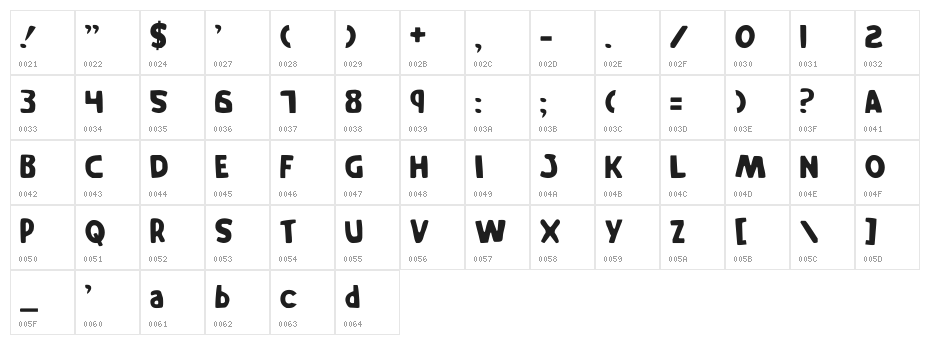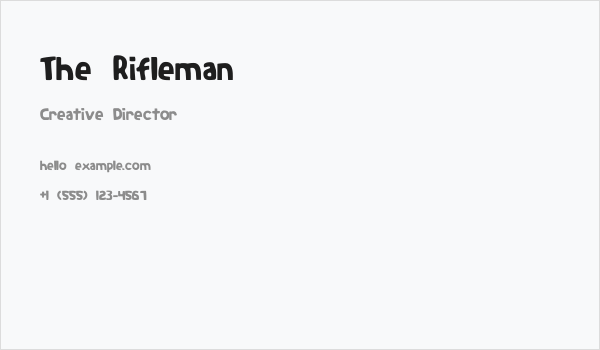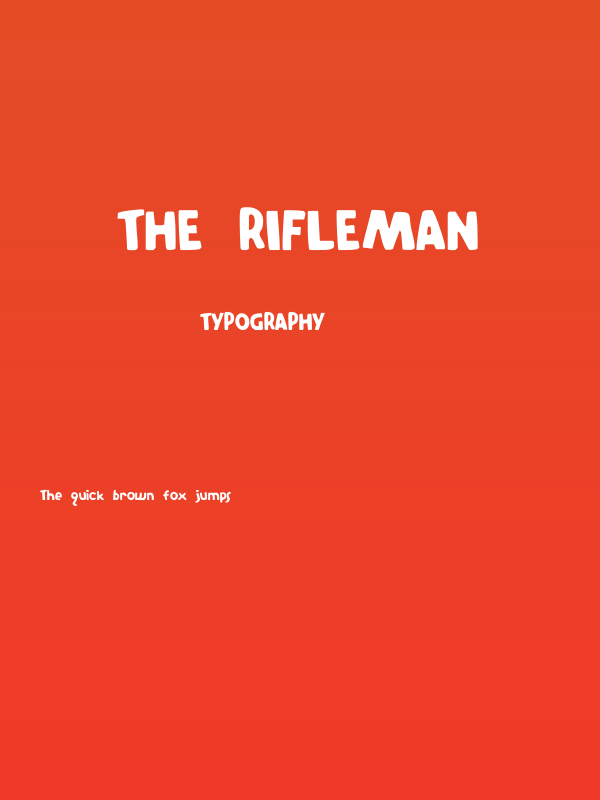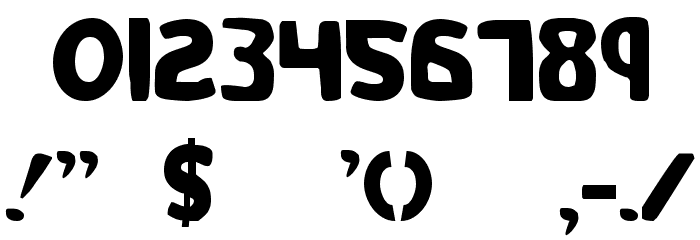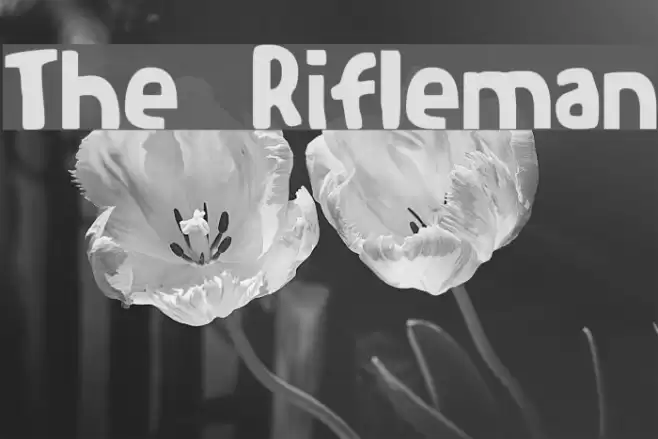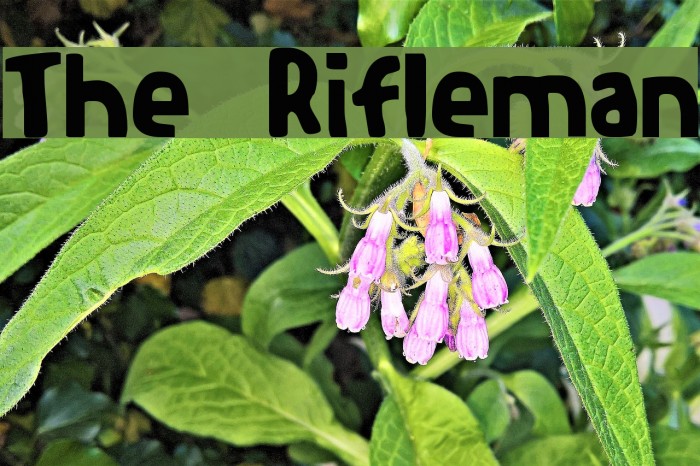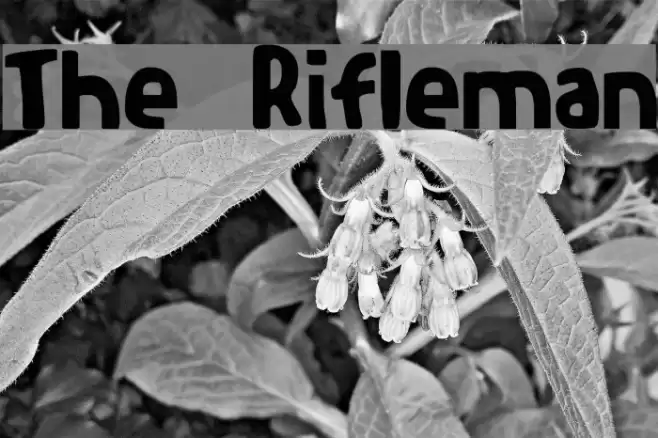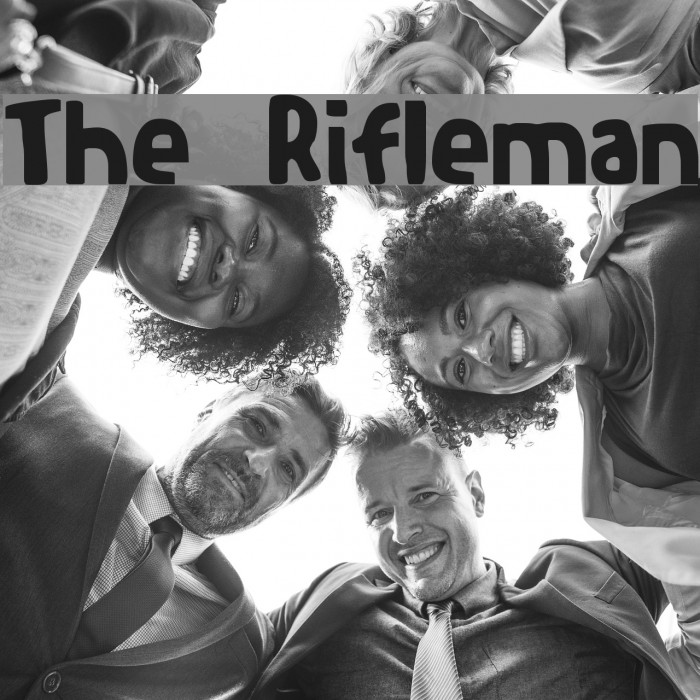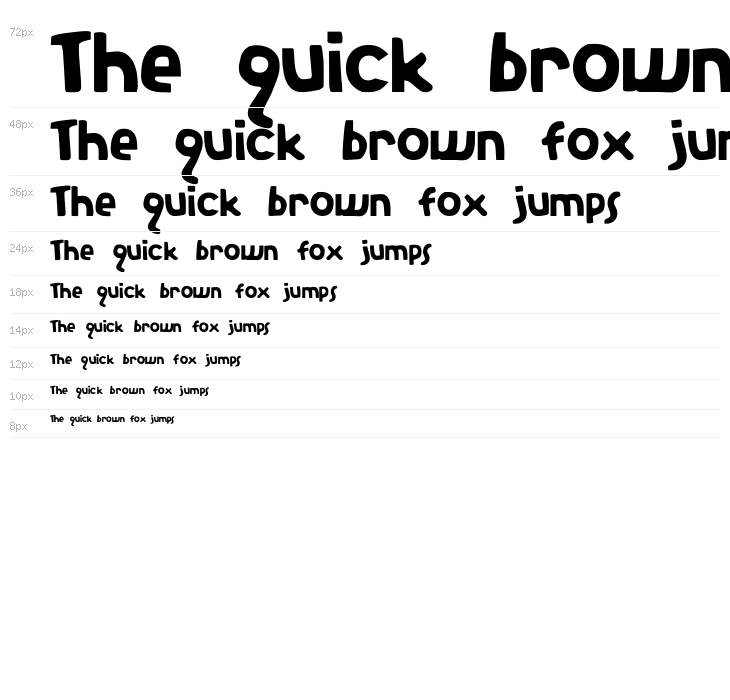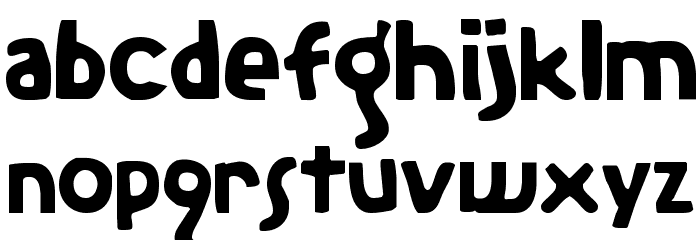
The Rifleman Font
✎ Script
| النمط العام | Playful, Whimsical |
| مشاريع مقترحة | Ideal for children's books, playful branding, posters, and creative social media graphics. |